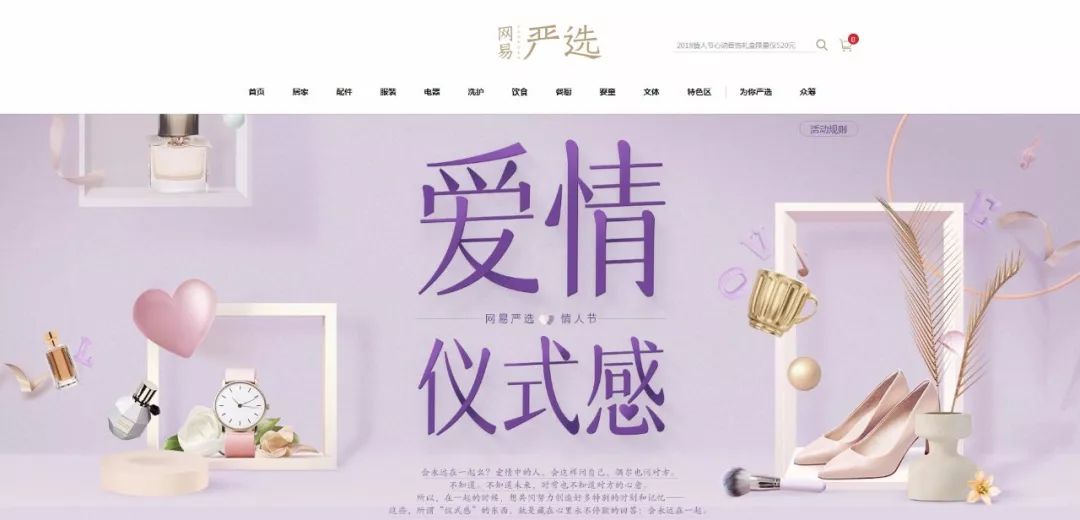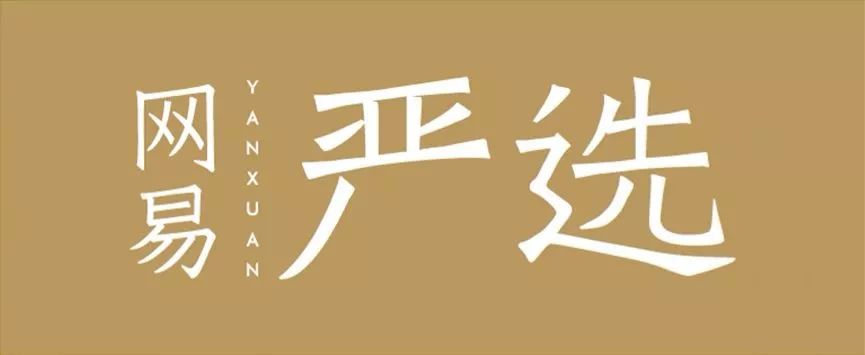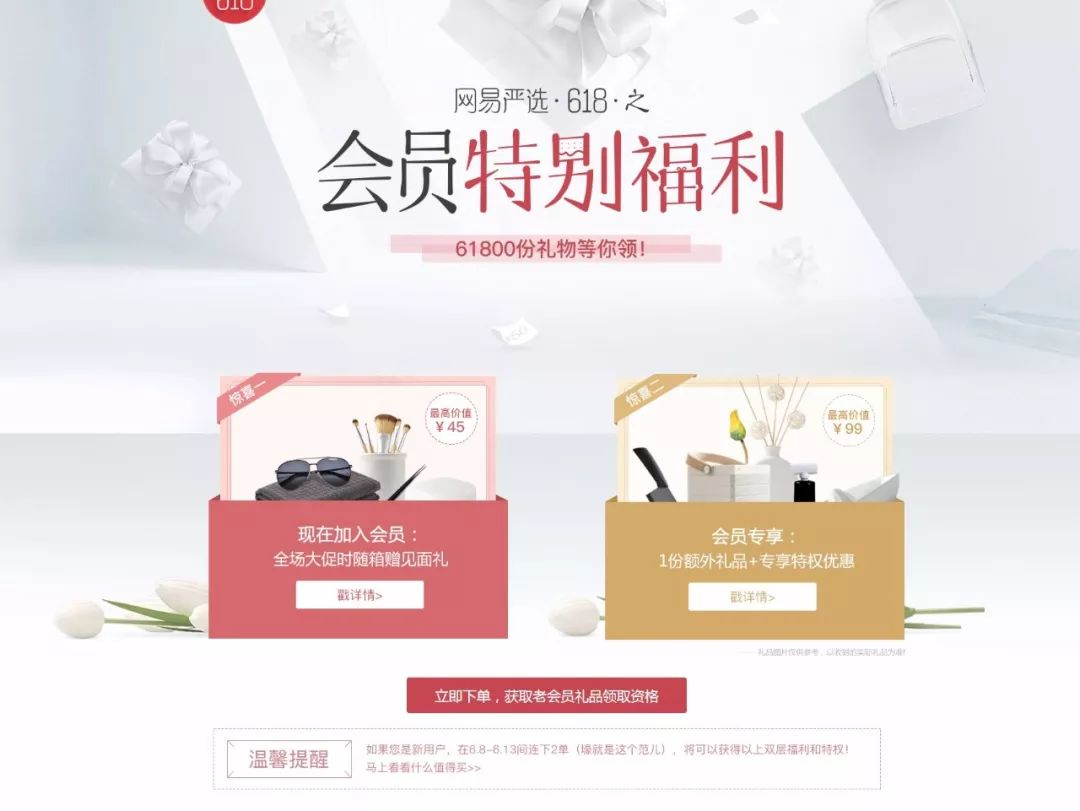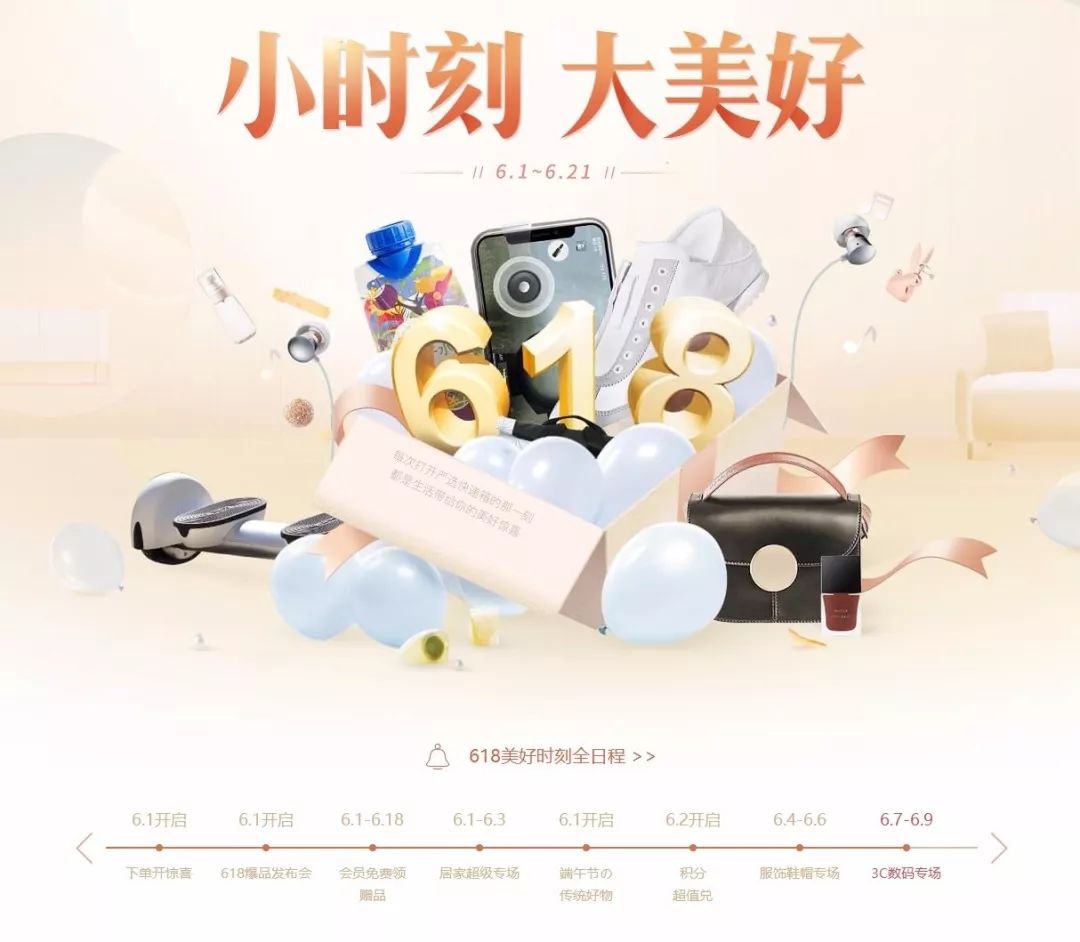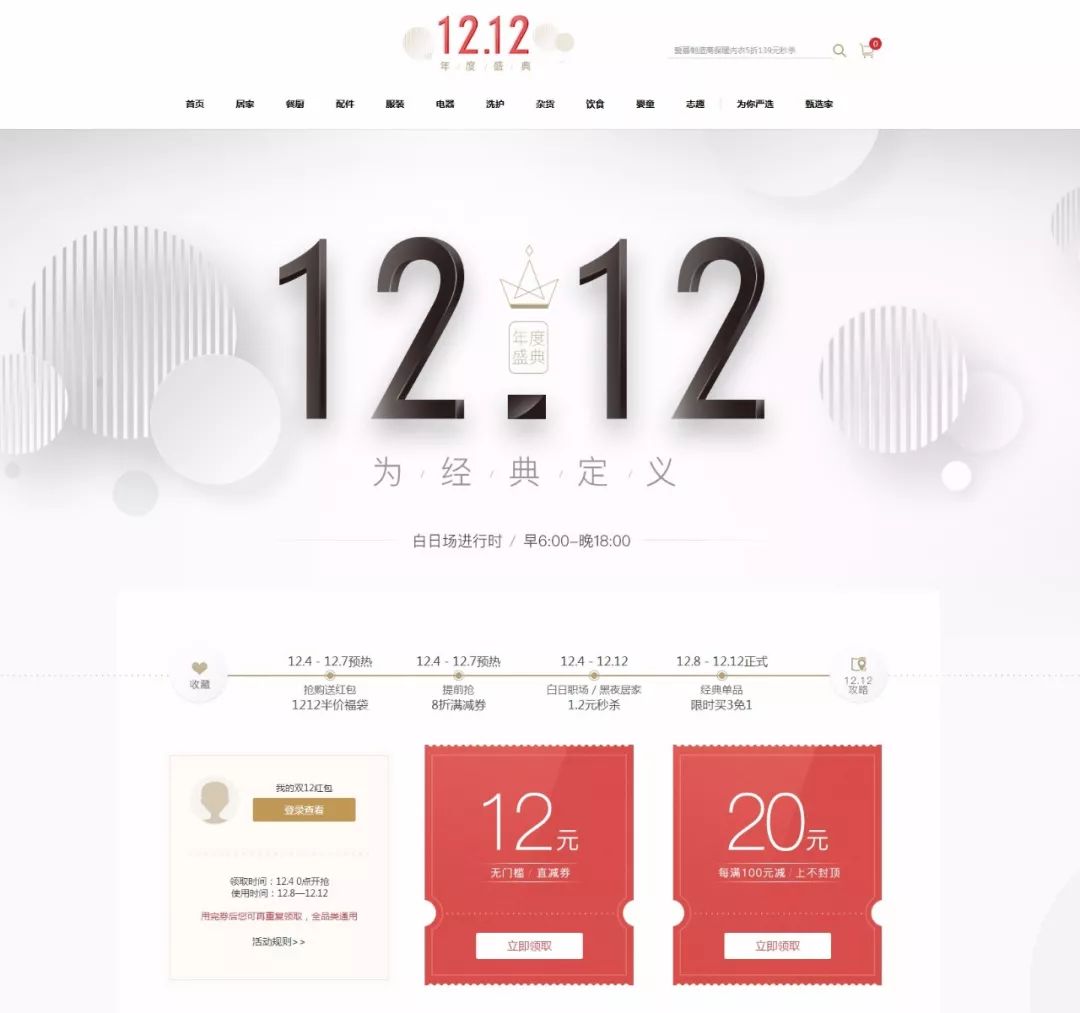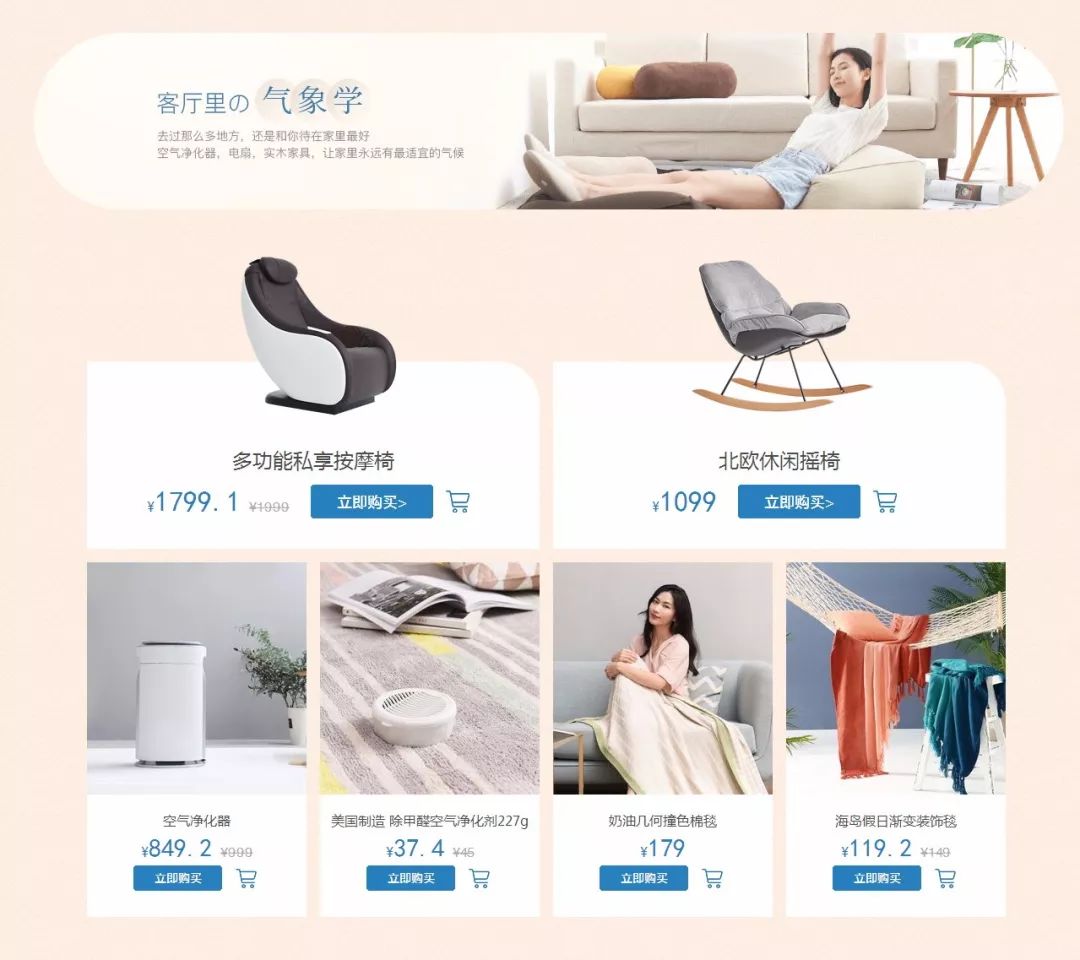
只需掌握这4点,就能做出网易严选风格的海报
电商每月都有活动,但是活动页一定是大红大黄吗?
国内有家电商平台特别吸引我的注意,之前有人称它们风格为“性冷淡风”,哈哈哈哈。
它就是咱们今天的主角,网易严选。
网易严选页面的背后,有哪些值得我们借鉴的点,我们又如何做出他们这种风格的作品?往下看。
严选是网易自营的电商平台,目前主营以家居产品为主,目标受众以追求品质的小资文艺青年居多。
网易严选的设计,自成体系,页面淡雅、文艺,甚至有些日式的性冷淡,画面细节很多。
今天我从4个方面跟你分享,如何做出一张网易严选风格的图?
||  一、淡雅低饱和的颜色
你可能会问,他们为什么用这种色调呢?是因为这类颜色好看?或者设计师的喜好?
并不是。
上面说过,网易严选的产品和人群定位是文艺小资,有一定品质感的产品。所以跟淘宝的大众促销是不同的定位路线。
其实这一点从网易严选的楷体logo也可以感受的出来。
咱们看看同样是618海报,淘宝天猫的海报颜色非常艳丽,纯度很高
网易严选哪怕是大促活动,相比之下还是很素雅..
还是那句话,战略定位决定执行。定位决定了设计,决定了文案等等后续的所有东西。
下面咱们看看网易严选常用颜色,大多页面都是淡雅浅背景色。这种色调是这类文艺人群定位的最佳选择。
背景色大多在拾色器左上角位置,低饱和、高明度。
文字的颜色,则饱和度和明度会低一些。
目前严选活动页无论背景还是文字,很少见用高饱和度颜色的,全是中低饱和色。
|| 二、宋体为主标题的文字
由于定位于文艺小资。所以严选中宋体字的出现频率相当高。少部分是楷体和黑体。
下面是网易严选常用的宋体标题汇总:
小塚明朝体
方正清刻本悦宋简体
方正标雅宋
汉仪瑞意宋
文鼎书宋简
蒙纳简中秀明体
中華民國字體  /  文悦古体仿宋
||  三、文字排版灵活,细节丰富
第三个是排版。
网易严选主营以家居产品为主,所以不会像苹果小米那类数码产品做的这么极简。
严选的排版经常会见一些小装饰,凸显温馨和趣味性。
文字排的非常灵活,啥样的都有。
下面给你介绍2种好借鉴的严选常见排版。
第一个是卡片形式。
这种排版布局简单上手,很容易出效果。
一般是一个主标题,加上一个条幅式的副标题构成。白色卡片周边可以用点线装饰下。
还有一种是大众排版。这种排版格式整个电商行业都在用,非常常见。
一般是一个主标题加一个利益点的框框。
不过严选的文案部分经常会加一些小细节。用(点/圈/斜线等)进行装饰,这点很值得借鉴。
虽然细节都不起眼,但是看着不会单调。
||  四、图案装饰
严选主营是家居生活产品,所以经常会用一些好玩的图案去装饰和丰富画面。营造轻松的家居气氛。
当然图形肯定都是和文案主题相契合的
加这些小图案,画面显得很轻松、活泼
那我不会画这样的图形咋办?
想要什么图标直接去花瓣搜就有,也可以去Iconfont阿里图标库,一搜一大堆。
除了上面这种实物型的图案外,严选还经常简单的几何图形。
比如圆形/三角/斜线线条等,作为纹理置于背景层,目的也是丰富画面。
下面通过一个案例操作下。用之前一个粉丝朋友做的锅的海报。
用他的素材和产品,文案都不变。
改了一下,是不是另一种感觉。这种几何场景在严选的页面中满常见的。
技术实现上没什么困难,小的产品可以找一些图标参考,用钢笔工具画即可。
大场景的话,可以找实物去参考。
我做的这张背景的橱柜,我就找了一个橱柜图照着轮廓画的。
综合以上几点,其实关键就是色调淡雅、配合宋体、排版加细节,以及图形装饰。
工作当中经常有老板,要求模仿别人家店铺的风格。
大多就是从这几点入手。(色彩、版式、字体、图形)看看别人怎么用的,跟着去练一段时间。
万变不离其宗。